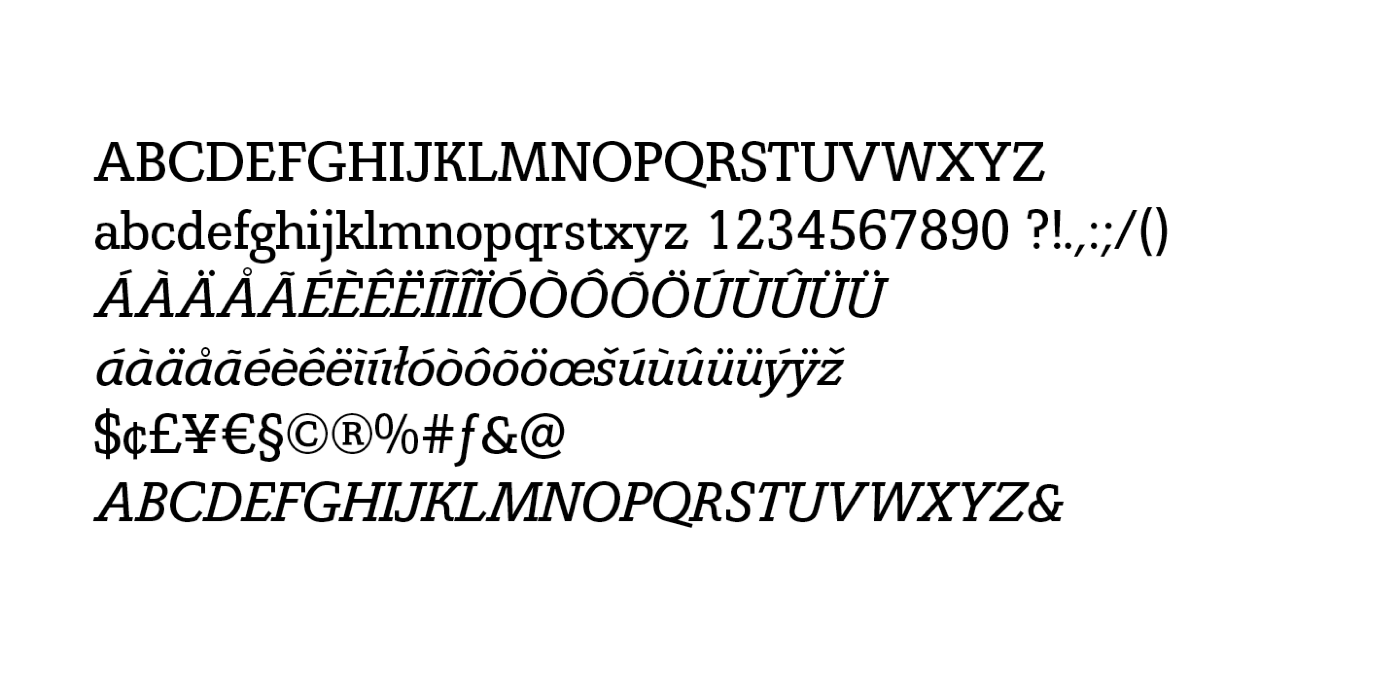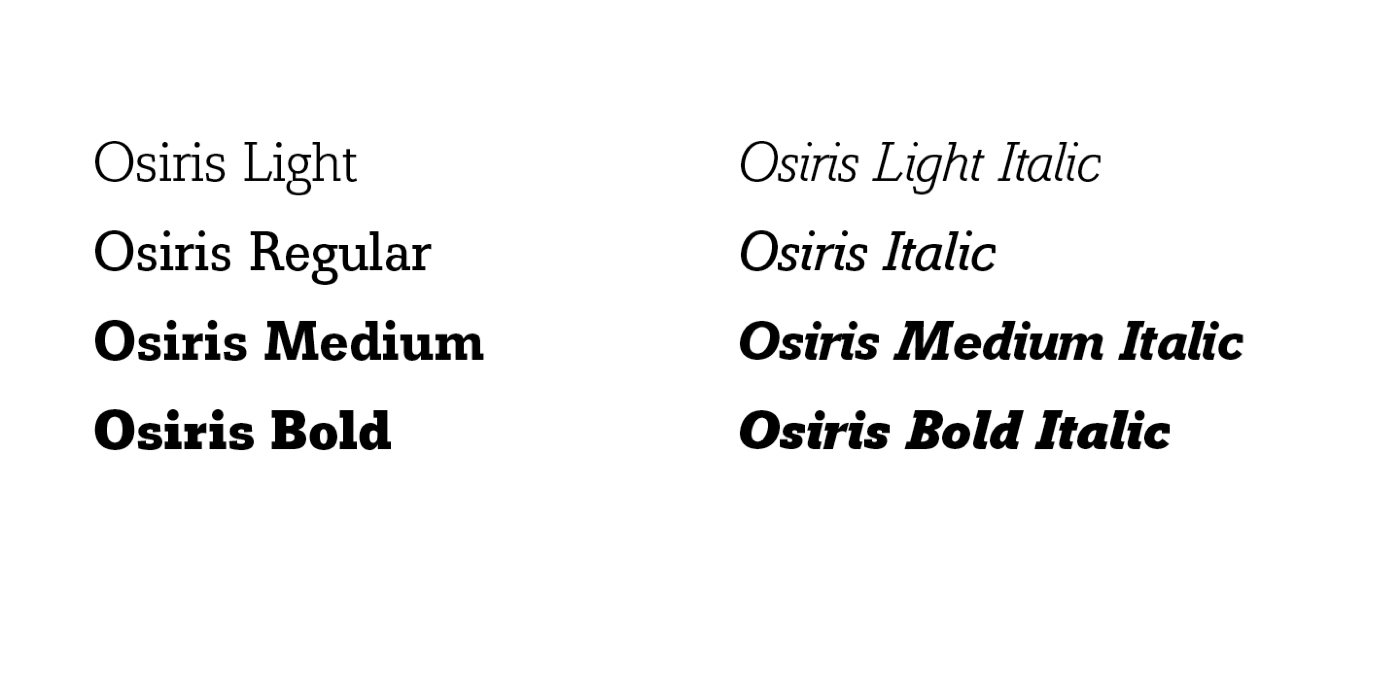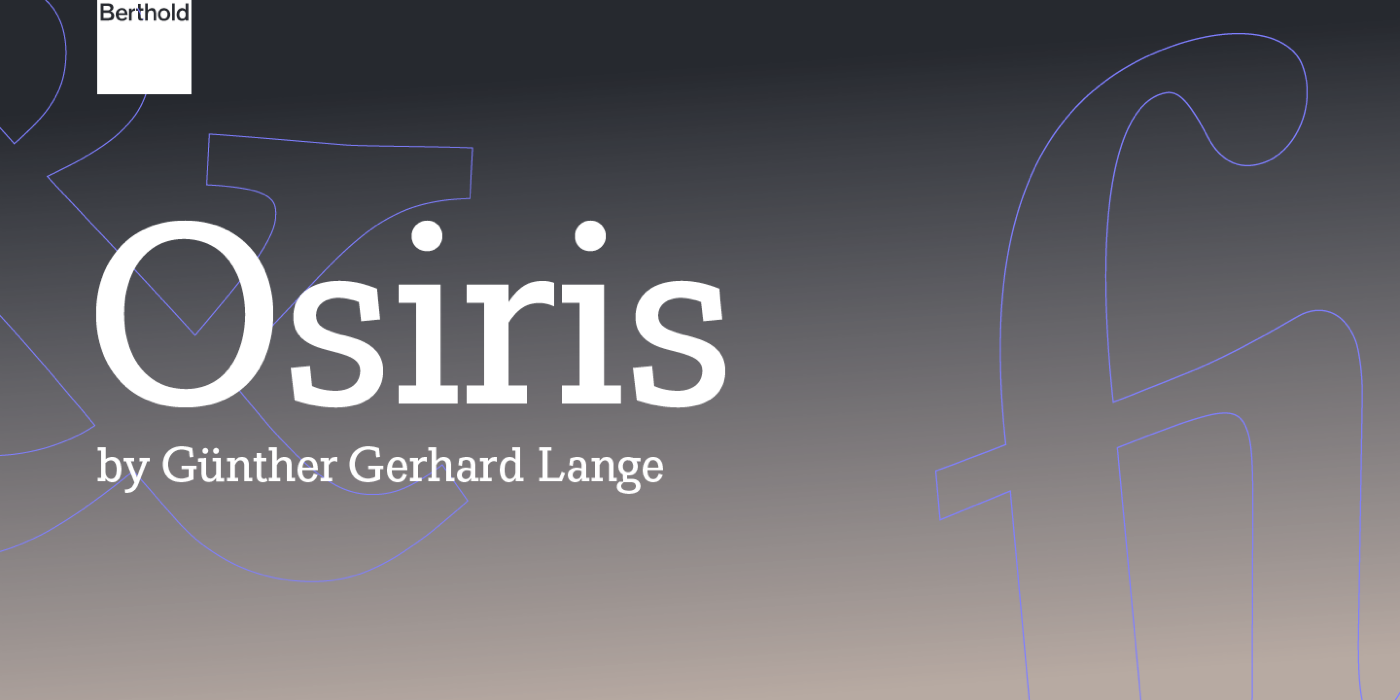
Font-Wiki: Osiris (Berthold)
Die Osiris ist eine serifenbetonte Antiqua-Familie von Gustav Jaeger aus den 1980er-Jahren. Die Schrift verfügt über vier Strichstärken mit Kursiven und ist heute mit westeuropäischer Belegung über Monotype verfügbar.